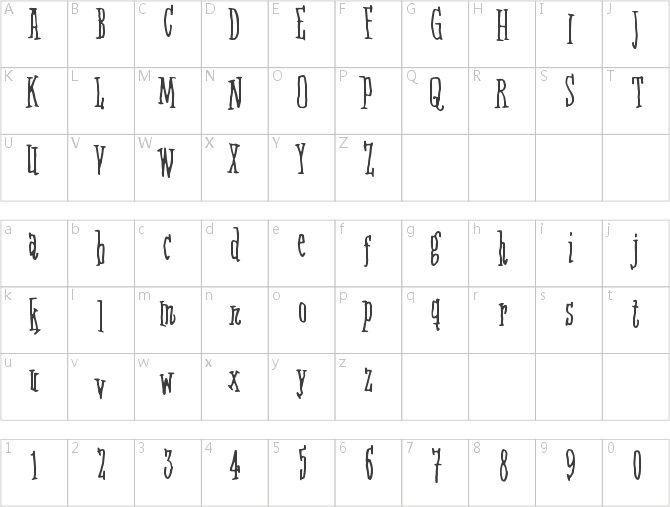
字體名稱: Fifteen
Fifteen Feet Of Pure White Snow
Fifteen Feet Of Pure White Snow字體字庫是一款讓人賞心悅目、百看不厭的英文字體,適合各類廣告和產品包裝設計應用,字體大小0.03MB,格式為ttf字體,上傳用戶是速拓科技,作者/版權方為未知